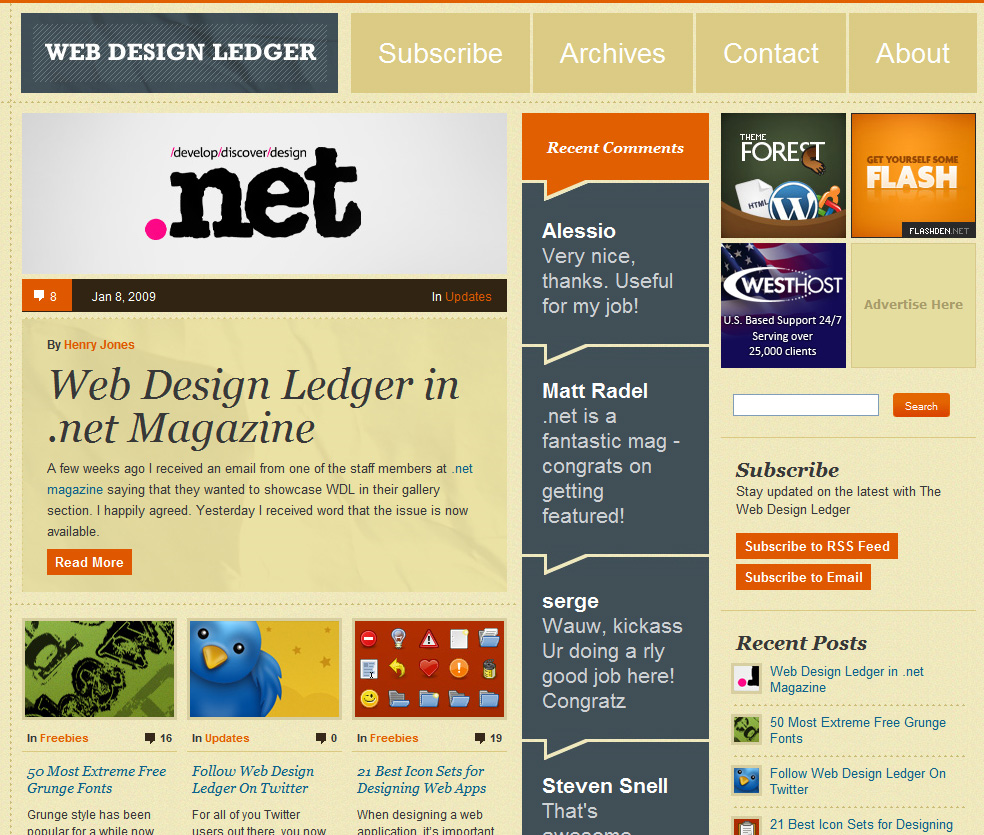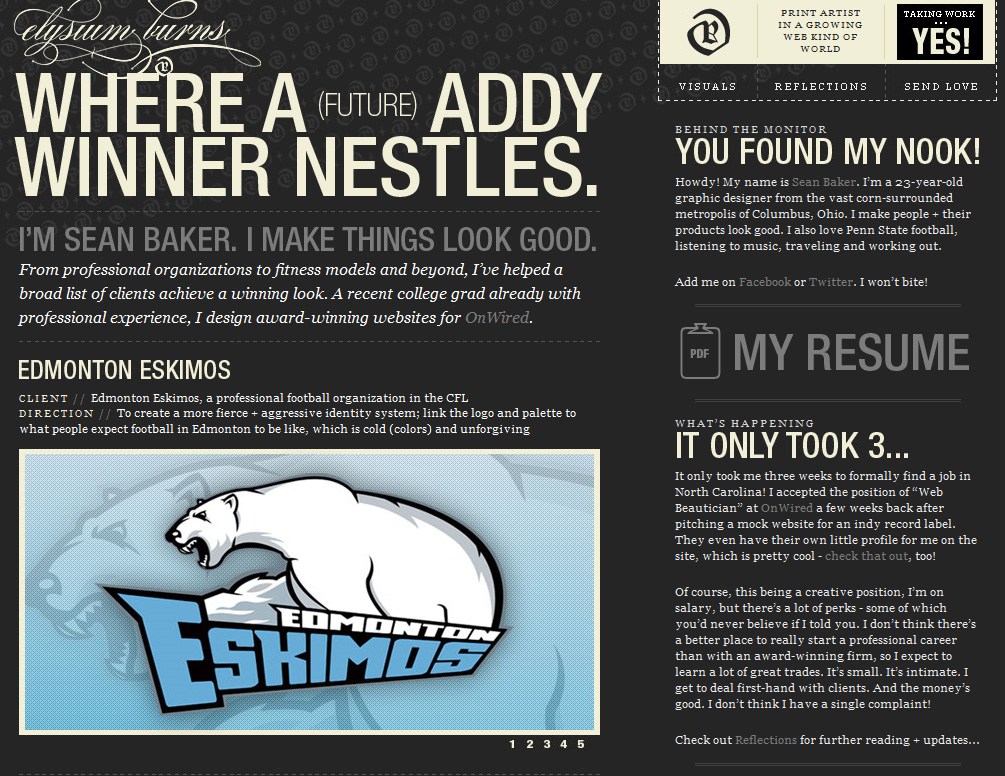
Selección de 20 sitios Web con bonita tipografía
La tipografía en diseño web juega una parte integral para establecer el tono, tema y mensaje de un sitio web.
Por ejemplo, puede transmitir un punto de atención a la modernidad o tradicionalismo simplemente utilizando un tipo de letra
serif o
sans serif, respectivamente. Puede llamar la atención sobre determinadas partes del contenido, y ayudar al pasar a otros, al cambiar el color de la letra, la línea de altura, estilo y tamaño. Una efectiva de la paleta de tipos de letras que no sólo tiene un diseño atractivo, sino que también contribuye a la legibilidad y facilidad de uso del contenido.
En el artículo
20 Websites with Beautiful Typography , tenemos una buena selección con gran variedad de sitios que muestran los usos funcionales y creativo de la tipografía que son realmente un ejemplo a seguir, te recomiendo que le des un vistazo a cada una de las páginas:
1. Jason Santa Maria
2. Elysium Burns
3. GOOD
4. Web Design Ledger
5. Future Of Web Apps
6. VigetInspire
7. Diaroogle.com
8. The Morning News
9. Ordered List
10. Words Are Pictures
11. Meagan Fisher
12. The New Yorker
13. Black Estate Vineyard
14. Ad Fed MN
15. What a Lovely Name
16. Rustin Jessen
17. The Darling Tree
18. I Love Typography
19. A List Apart
20. Training by Collective Idea